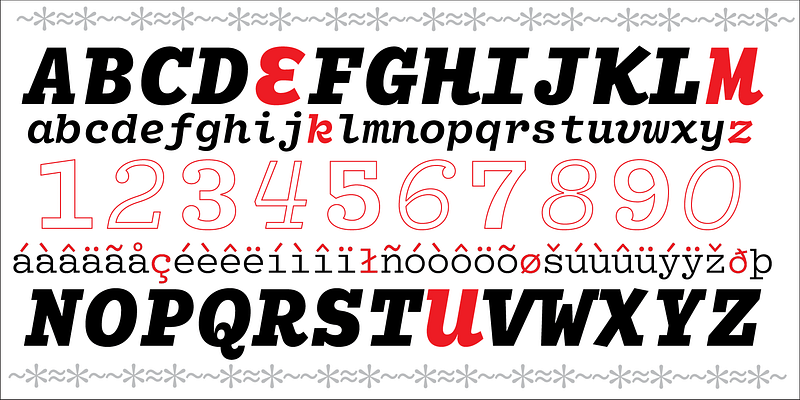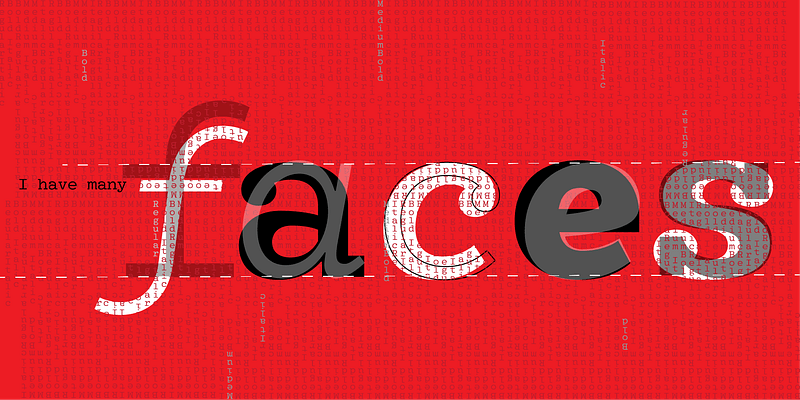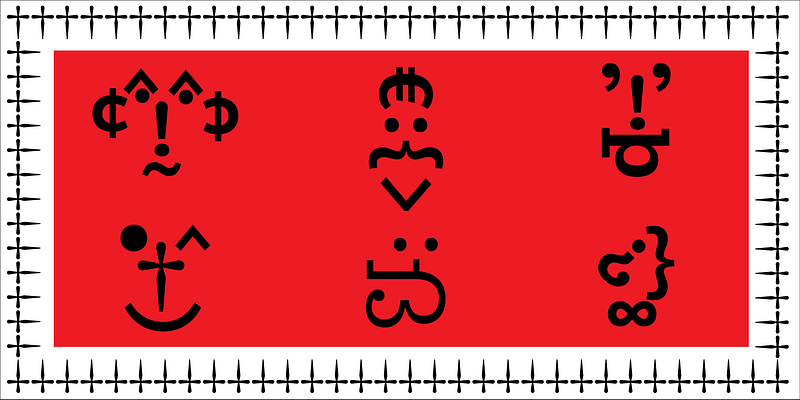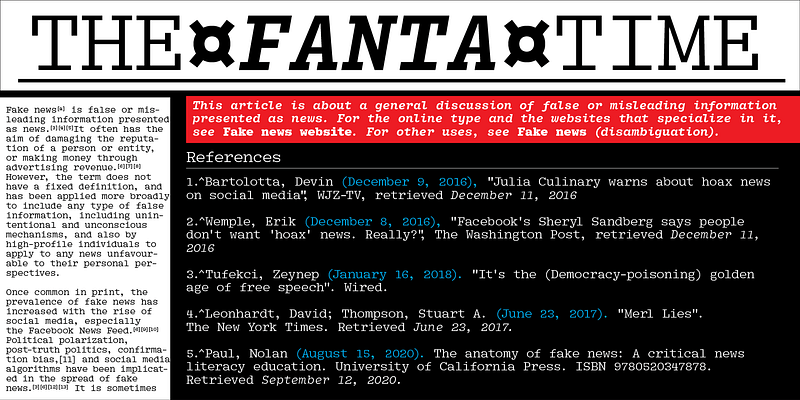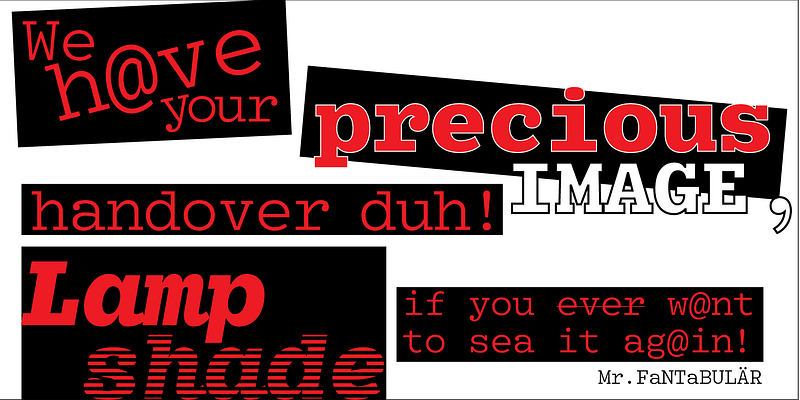
MVB Fantabular prouve que les polices à espacement fixe n’ont pas besoin d’être formelles ou ordinaires. Inspiré par les lettres des anciennes machines à écrire, Akemi Aoki a conçu une famille ludique de trois graisses en italique. Chaque caractère possédant la même largeur, MVB Fantabular convient partout où une police à espacement fixe est nécessaire, mais la police est si libre et nonchalante qu’elle dissimule parfaitement sa construction fixe, ce qui lui permet également d’être utilisée dans divers contextes. Une version sans empattement, MVB Fantabular Sans, est également disponible.